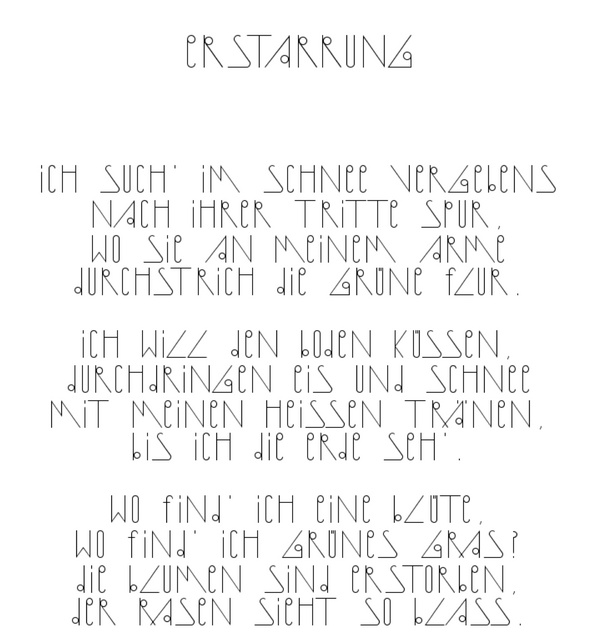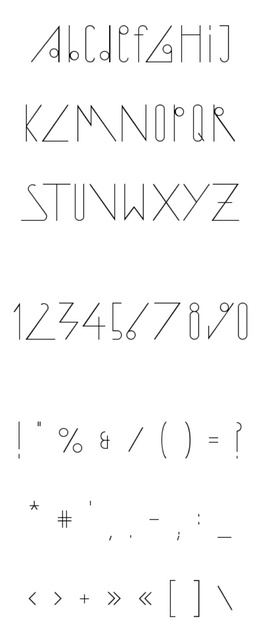
Grundsatzentscheidung Hinting/Mastering
seit einiger Zeit bin ich am Schriftentwerfen und habe mittels FontForge schon ein paar gute Ergebnisse erzielen können. Nun will ich eine kommerzielle Verwertung ins Auge fassen und da stehe ich vor einer Grundsatzfrage zu der ich ein paar Expertenmeinungen brauche. Es geht um das Hinting bzw. das Mastern der Schriften. Die reine Erstellung der Glyphen und das Programmieren der Unterschneidungen (auch in Paaren) ging mir gut von der Hand, alles weiter würde ich gerne anderen überlassen. Ich bin selber kein Anwender und das erste Einlesen in die Hinting-Problematik habe ich schon nur halb verstanden und ich glaube auch nur begrenzte Freude daran zu finden. Mir fehlt das Verständnis und das Wissen für Bildschirmdarstellungen und auch worauf ein Profi Wert legt.
Nun will auch kein halbes Zeug anbieten sondern wirklich brauchbare Arbeiten. Wer macht so etwas? Ich stelle vor allem auch deshalb die Frage weil das ja scheinbar einen großen Aufwand bedeutet. Ich kann mir nicht vorstellen dass sich das bei den Lizenzpreisen für eine spezielle Schrift finanziell wirklich lohnt.
Ich habe hier mal ein Beispiel meiner Arbeit. Ich mag besonders markante und eigenwillige Versalienschriften. Dafür habe ich jede Menge guter Ideen. Es ist aber nicht ausgeschlossen auch mal eine „komplette“ Schrift zu erstellen.
Ich will mir bald FontLab zulegen und die Sache professioneller angehen. Wer hat einen Tipp? Gibt es so etwas wie einfaches Hinting das auch ein Laie gut hinbekommt oder ist der Weg über einen Spezialisten sinnvoller (und wenn ja wo sind die)?
Chronograph
Keine Expertenmeinung, aber:
Es gibt verschiedene Intensitäten, mit denen Du Hinting betreiben kannst, mit stark unterschiedlichem Aufwand und Effekt.
Auf der untersten Stufe steht das Markieren von Stämmen (das, was FontForges AutoHint tut) und das Einstellen von BlueValues bzw. Ausrichtungszonen. Bei den meisten Schriften kann dies weitgehend automatisiert werden und ist selbst, wenn man es komplett von Hand macht, recht wenig Arbeit. Zusammen mit automatischen Instructions (z. B. durch ttfautohint) dürfte dies für alles außer Brotschriften, welche auch bei kleinen Auflösungen bzw. Schriftgrößen eingesetzt werden sollen, einen vernünftigen Kompromiss zwischen Aufwand bzw. Kosten und Nutzen darstellen.
Gerade bei der Beispielschrift (sowieso nur höheraufgelöst einsetzbar; konstante Strichdicken; dünne, einfache, klar abgegrenzte Formen) halte ich mehr für übertrieben. Im Beispielbild würde mit Hinting übrigens vermutlich jeder horizontale und vertikale Strich genau einen Pixel breit sein statt über mehrere Pixel „aufgeweicht“ zu sein.
Wahrscheinlich sind mindestens 95% der Schriften im Umlauf nicht manuell gehintet. Ausnahmen sind Systemschriften und gegebenenfalls Office-Schriften, die speziell auf kleine Größen in (älteren) Windows-Umgebungen ausgelegt sind.
Ansonsten geht es beim üblichen Auto-Hinting darum, Stämme und vertikale Linien möglichst homogen erscheinen zu lassen. Das geschieht durch saubere Anordnung der Punkte selber und durch Vorgabe von Zonen, in die diese Punkte fallen. Damit dann zum Beispiel nicht bei einem O plötzlich ein ganzer Pixel mehr in der Höhe benutzt wird, als bei H.
Das ist aber alles kein Zauberwerk und insbesondere bei Display-Schriften (wie deiner) alles überschaubar.
scheint ja weniger gefährlich zu sein;
d.h. ich kann eine wie die dargestellte Schrift mit homogenen Stammbreiten und Zonendefinitionen getrost anbieten;
dann werde ich mich ins Hinting einlesen.
d.h. ich kann eine wie die dargestellte Schrift mit homogenen Stammbreiten und Zonendefinitionen getrost anbieten;
Nur zum Vorbeugen von Missverständnissen: Automatisches Hinting mit kurzer Kontrolle sowie Einstellen von BlueValues wäre schon gut (und dauert allerhöchstens eine Stunde). Das Beispiel oben sähe mit Hinting sicher deutlich besser aus (wobei es hier aber sehr gut sein kann, dass der Bitmap-Konverter schlichtweg überhaupt kein Hinting unterstützt).
scheint ja weniger gefährlich zu sein;
d.h. ich kann eine wie die dargestellte Schrift mit homogenen Stammbreiten und Zonendefinitionen getrost anbieten;
dann werde ich mich ins Hinting einlesen.
Anbieten kann man auch einen ungehinteten Font; natürlich. :-)
Beim Hinting geht es ja ausschließlich darum die Lesbarkeit und den visuellen Charakter einer Schrift in allen Schriftgrößen und allen Ausgabemedien zu erhalten.
Das Automatische Hinting (in FontLab) funktioniert nur halbwegs vernünftig. Und nur, wenn ich im Vorfeld bereits einige wichtige Vorgaben gemacht habe. Es ist besser als Nichts; allerdings (ich hab das TrueType-Hinting bei Linotype gelernt) ist das Automatische Hinting nur eine erste Hilfe und um die manuelle Nacharbeit führt kein Weg vorbei. Wie jede Facharbeit braucht auch gutes Hinting eine Menge Erfahrung. Viele Lösungswege erschließen sich nur durch Ausprobieren und stehen nicht in den Hintinganleitungen.
Ich empfehle daher den Gang zum Fachmann zu nehmen.